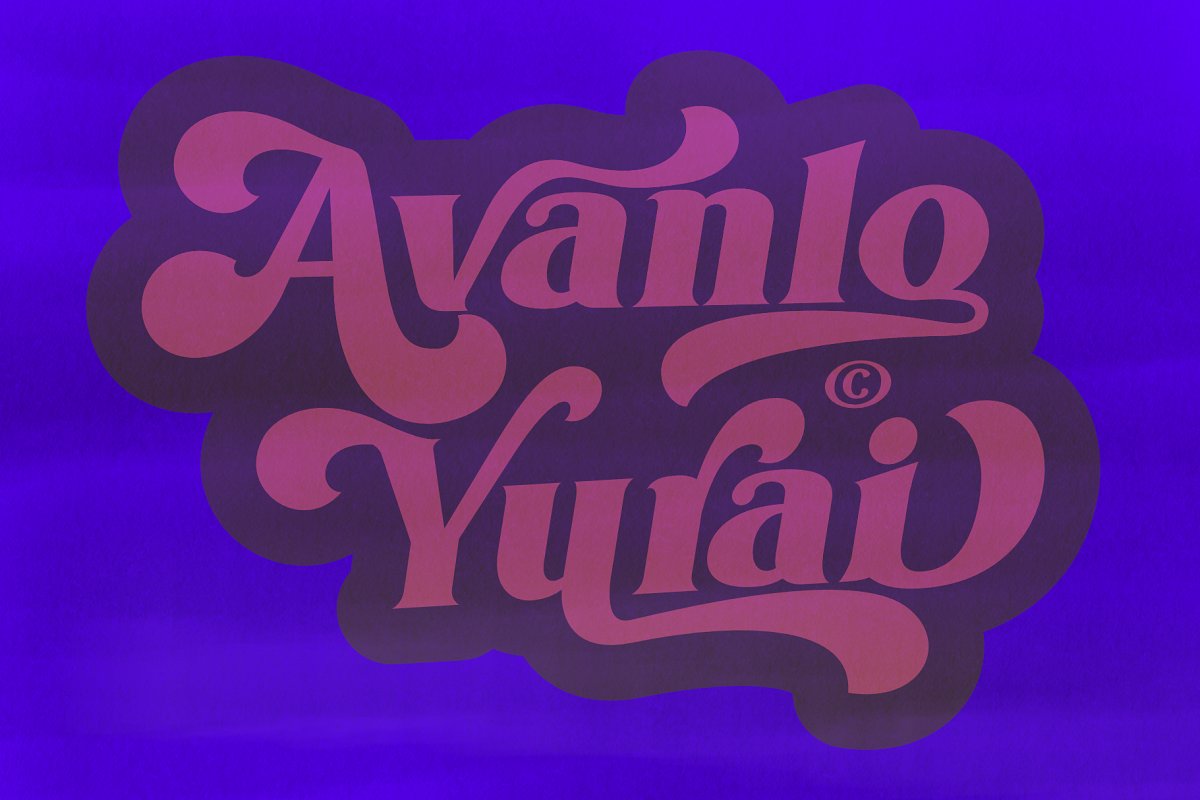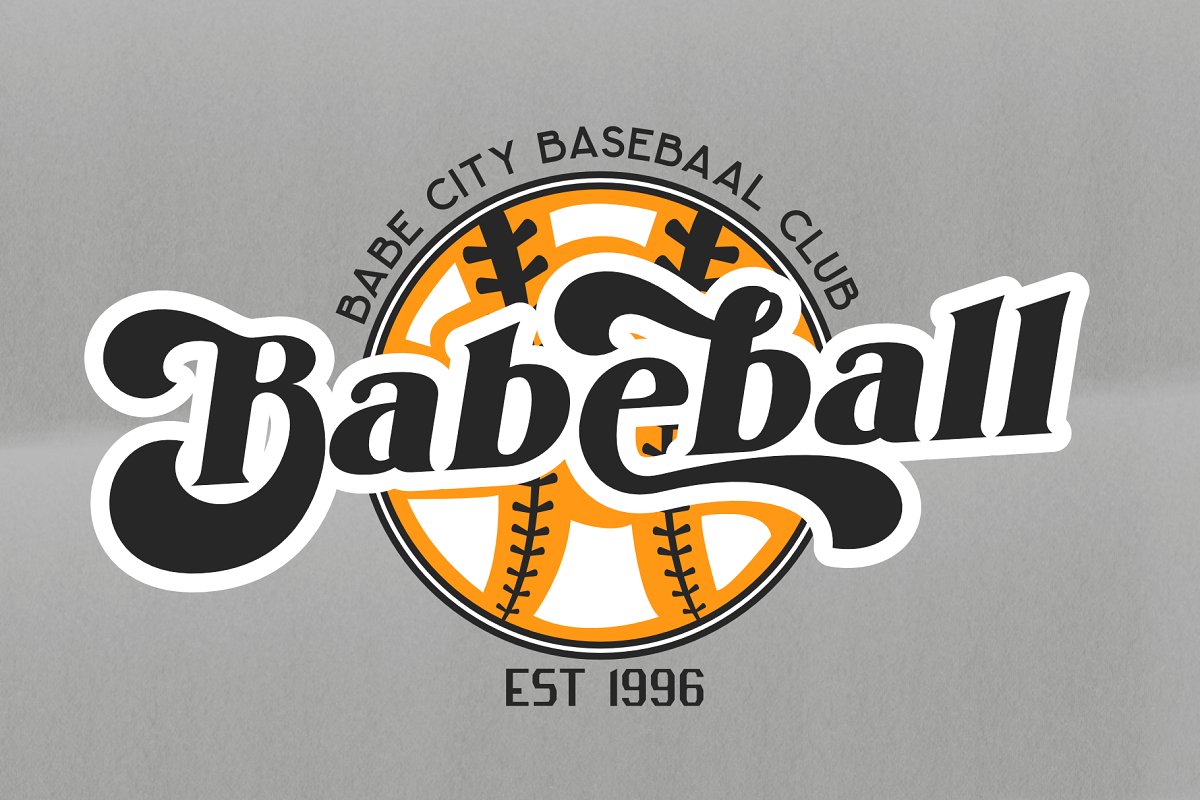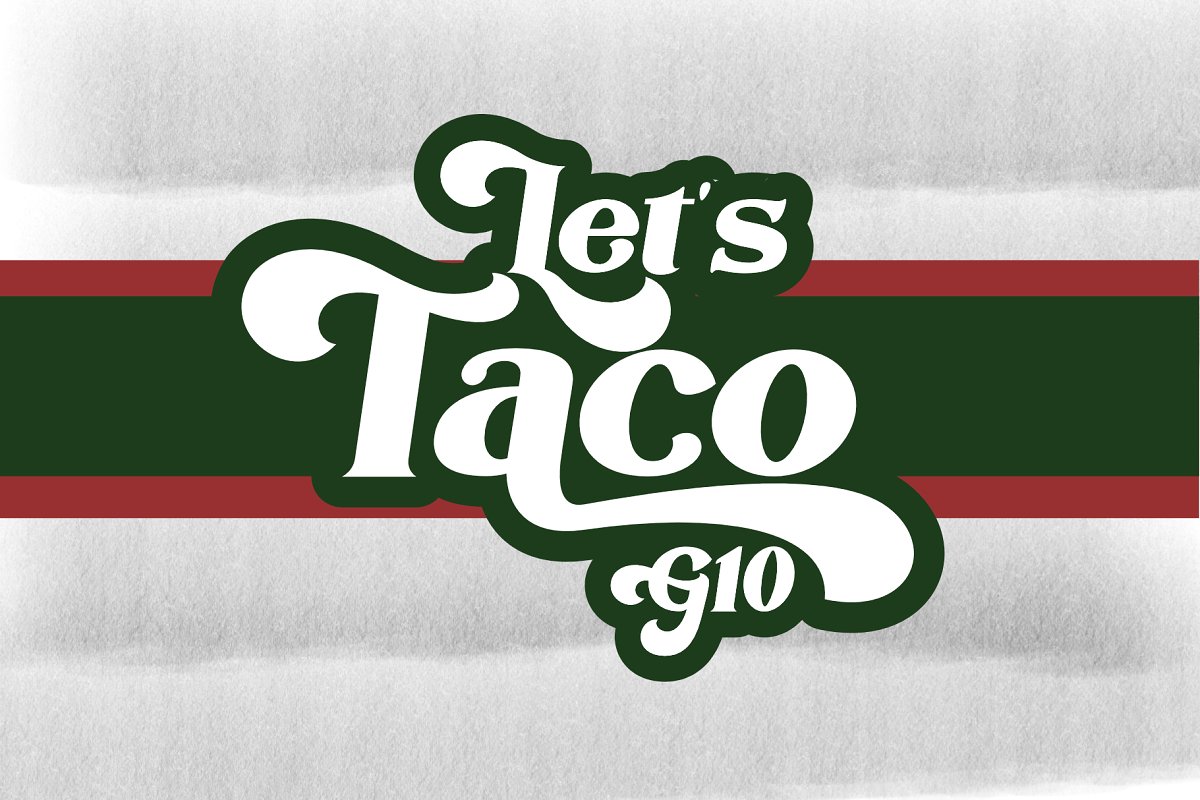
Karisma Font
Description de Karisma Font
Présentation de la nouvelle police Karisma, une police serif de style rétro inspirée des dessins typographiques des années 60 aux années 70, Karisma propose une variété de polices OpenType Features, afin qu’elle puisse vous aider à créer le design que vous souhaitez, alors qu’attendez-vous ? ?